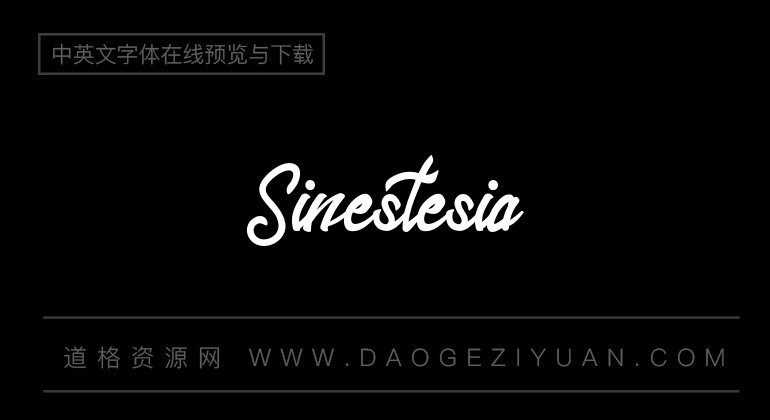
Sinestesia
? Sinestesia 字体是一款由西班牙设计师Juan Casco设计的自由字体,它具有轻巧现代的外观,拥有英文和拉丁字符,以及数字和标点符号。Sinestesia字体可以用于任何类型的技术,如网页设计,桌面出版,标牌和标识,甚至是艺术作品。它的设计简洁,字形精致,可以帮助设计师创造出独特的外观和感觉。
Sinestesia是一款非常不错的手写艺术字体,具有很好的视觉感,适合于文化类的宣传设计、商业类品牌的广告和产品包装设计以及个性化文字排版等较多场景。